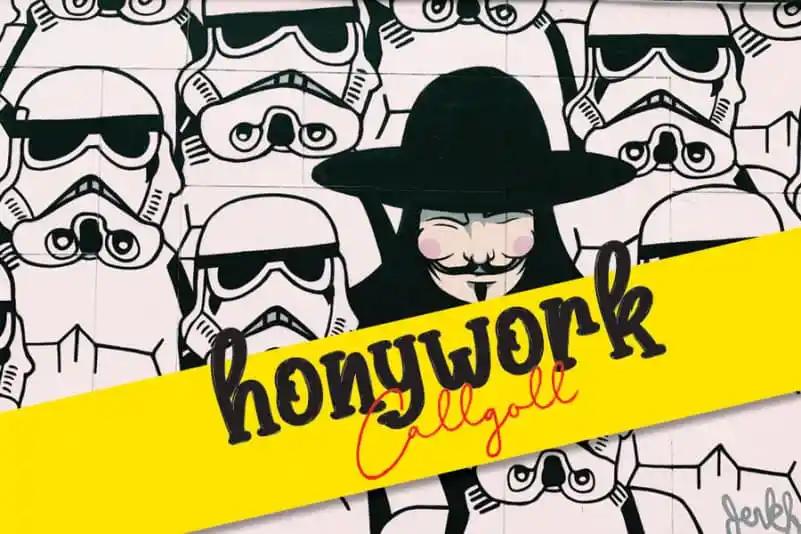
Honywork Handwritten Font – Download Grátis
A Honywork Handwritten Font é uma elegante fórmula de escrita manuscrita que se destaca por sua delicadeza e fluidez. Ela traz caracteres belos, com um equilíbrio perfeito entre as letras, o que a torna versátil para múltiplos projetos criativos. Adicione esta fonte à sua próxima ideia original e observe como ela ilumina seus designs, oferecendo um toque de charme e originalidade inigualável aos seus trabalhos. Ideal para designers buscando uma fórmula de escrita que enriqueça seus projetos sem comprometer a exatidão ou elegância. A Honywork Handwritten Font é perfeita para aqueles que valorizam um toque único em cada projeto, seja ele um logo detalhadamente pensado, um layout de site sofisticado ou uma capa de livro com o encantamento do realismo manuscrito.